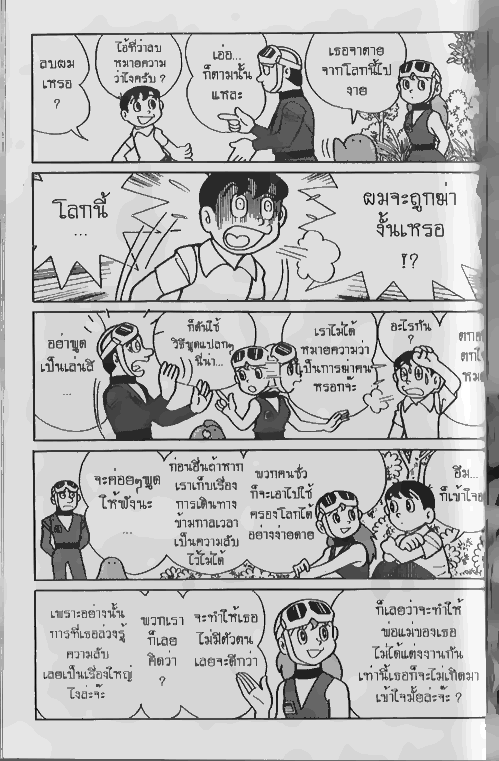
ant comic ใช้ฟ๐นต์ JPG ตูด้วยล่ะ
เห็นใช้มาหลายเรื่องละ (สระลอยด้วย  :29: )
วิบัติ วิบัติ วิบัติ
ไม่ได้วิบัตินะ ไอ้ตัวเมือกๆ นั่นมันเป็นตัวที่เวลาพูดจะลากเสียงยานคาง
ตัวไหนครับ
ตัวนี้ไง
ช่องแรก"เธอจาตายจากโลกนี้ไปงาย"
ขอบคุณครับ เห็นได้ว่ามีไอ้วิบัติเพียงตัวเดียวแสดงว่าอัตราส่วนยังน้อยอยู่ครับ